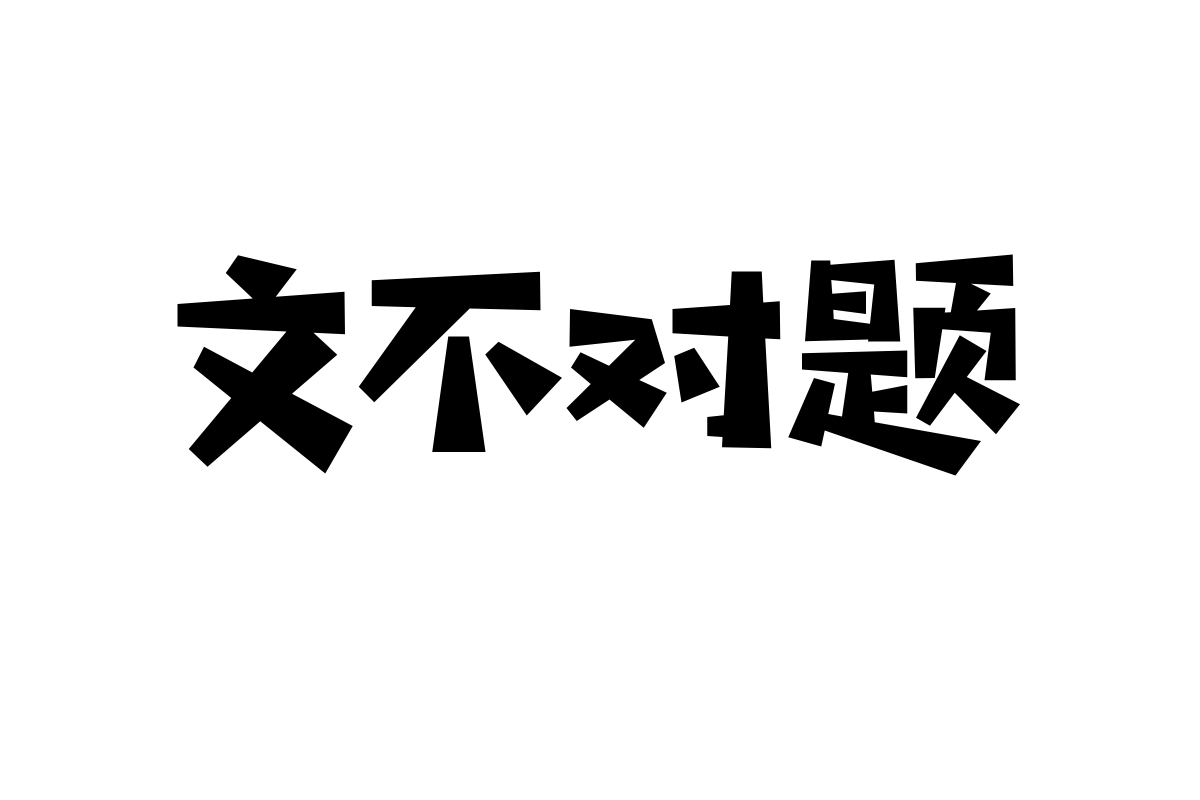
汉仪铸字木头人是一款具有独特风格的中文字体。这款字体的设计灵感来源于中国传统的木刻版画,将汉字的笔画与木刻版画相结合,展现出一种独特的艺术风格。
字体特点:
1. 字形结构:汉仪铸字木头人采用了传统的汉字字形结构,保留了汉字的基本笔画和结构特点。同时,通过模仿木刻版画的风格,使得字体在视觉上呈现出一种独特的质感。
2. 笔画处理:汉仪铸字木头人在笔画的处理上,注重细节和层次感。每个笔画都经过精心设计,既有传统的韵味,又不失现代感。同时,通过调整笔画的粗细、弯曲度等参数,使得字体在不同场景下都能呈现出不同的效果。
3. 字体风格:汉仪铸字木头人的整体风格独特,既有传统汉字的韵味,又融入了现代设计元素。这使得它不仅适用于传统印刷品,也适合应用于数字媒体、网页设计等多种场合。
4. 适用场景:汉仪铸字木头人适用于各种需要展现中国传统文化特色的场合,如文化宣传、广告设计、书籍装帧等。同时,由于其独特的风格,也适合用于个性化的产品设计、品牌标识等。
总之,汉仪铸字木头人是一套具有独特风格和实用性的中文字体,适合用于需要展现中国传统文化特色的场景。